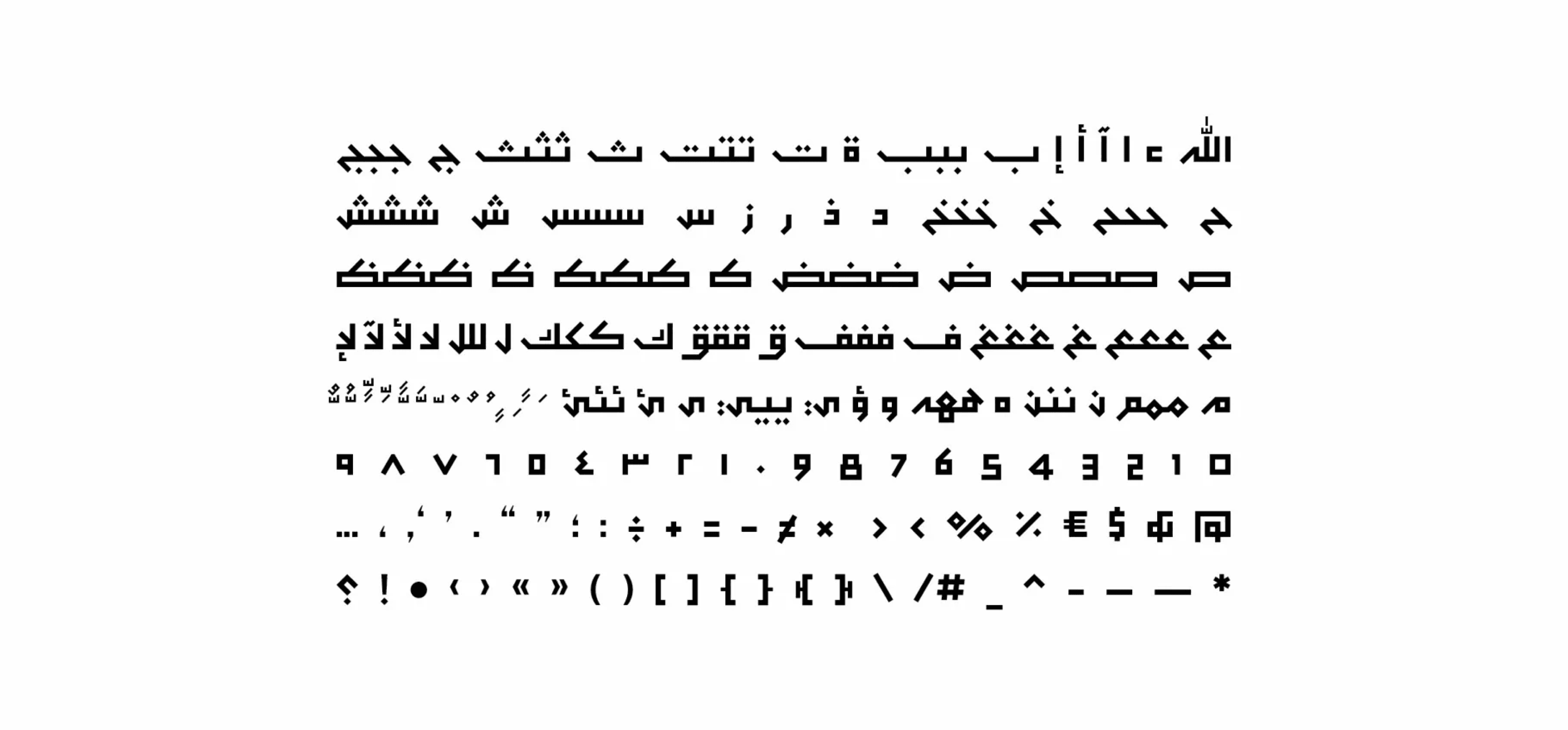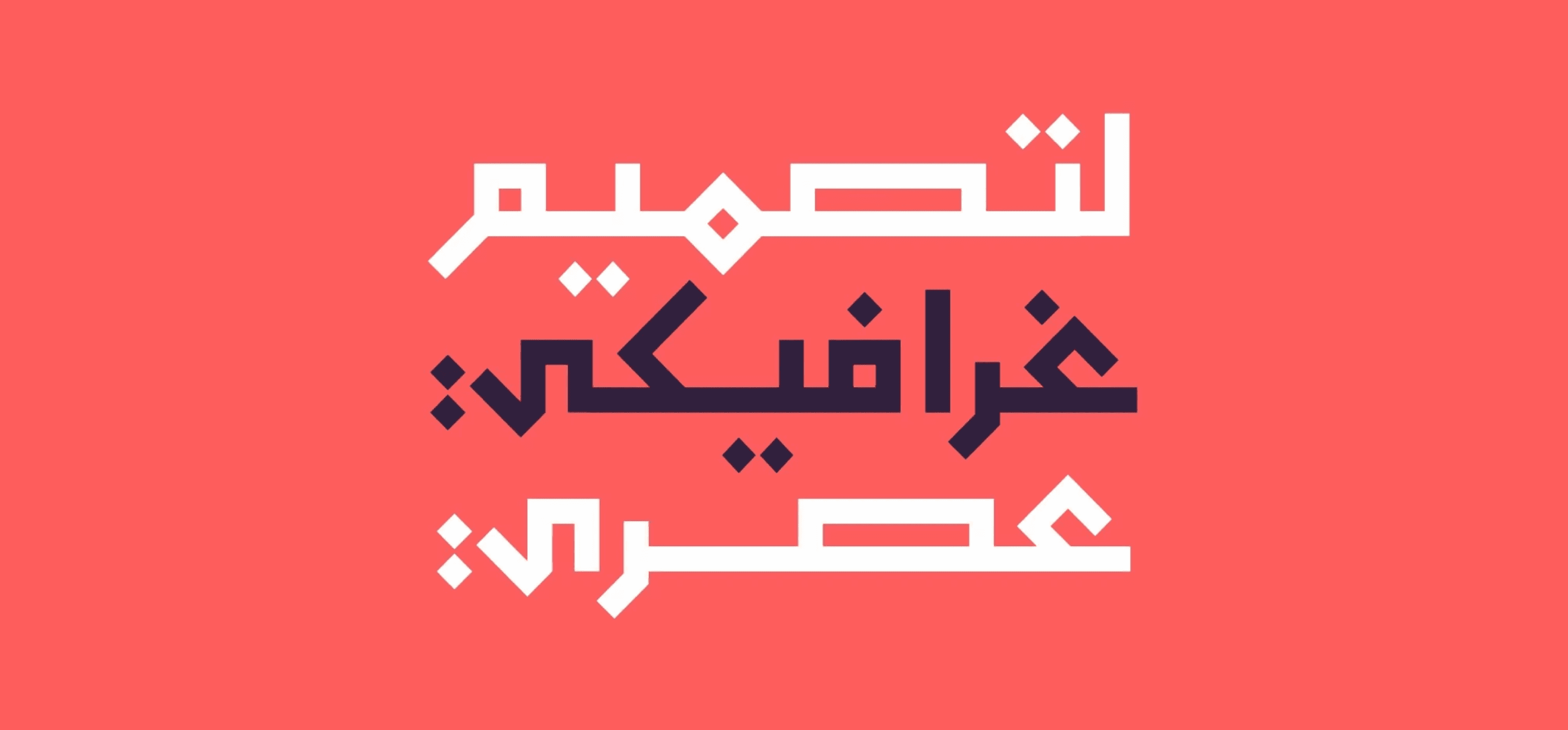
خط Monbasit (وهي كلمة عربية تعني "مُنبسِط") هو خط عرض عربي يتميز بأشكال حروف ممدودة وبنية هندسية واضحة. يستوحي تصميمه من مزيج بين الخط الكوفي القديم والكوفي المربع، مما يمنحه طابعًا تراثيًا بلمسة معاصرة.
يتوفر الخط بوزنين: عادي (Regular) وعريض (Bold)، ويُعد مناسبًا للمشاريع الإبداعية الحديثة مثل الهوية البصرية، تصميم الويب، والمطبوعات. كما يدعم أنظمة Windows وmacOS وتطبيقات الهواتف المحمولة، مما يجعله خيارًا عمليًا وجماليًا في آنٍ واحد.